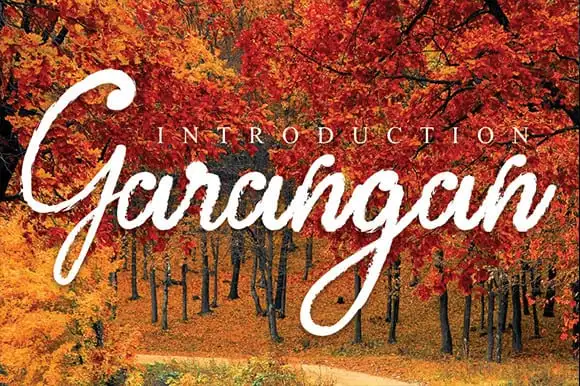
Garangan Brush Font – Download Grátis
A Garangan Brush Font é a escolha perfeita para quem busca uma tipografia que transmite elegância e personalidade. Especialmente projetada para aplicativos visuais variados, como displays de paredes, convites de casamento, identidades digitais, embalagens de produtos, logotipos de produtos, rótulos, fotografias e até mesmo marcas nas imagens, essa fonte é um verdadeiro atalho à criatividade. Com uma aparência autêntica e moderna, ela é perfeita para projetos que exigem um toque único do mundo da escrita a mão, tornando-a uma opção ideal para designers de todo o Brasil buscando adicionar personalidade a suas criações visuais. A Garangan Brush Font não apenas oferece beleza, mas também versatilidade, fazendo dela uma fonte indispensável no seu coquetel de ferramentas digitais.